新媒体行业对于花式字体的使用着实非常广泛,具有独特个性的创意花体字可以凸显整个文案和设计的风格。花体字最早是英文书法字体的其中一种,一般是用墨水卸载纸上,把纸贴在金属板上雕刻,然后复制印刷的。英文花体的显著特点是笔画有明显的粗细变化,线条设计复杂。中文的花体字,主要以花鸟的形象作为笔画的呈现。咱们一起来看看下面这两款字体图片。
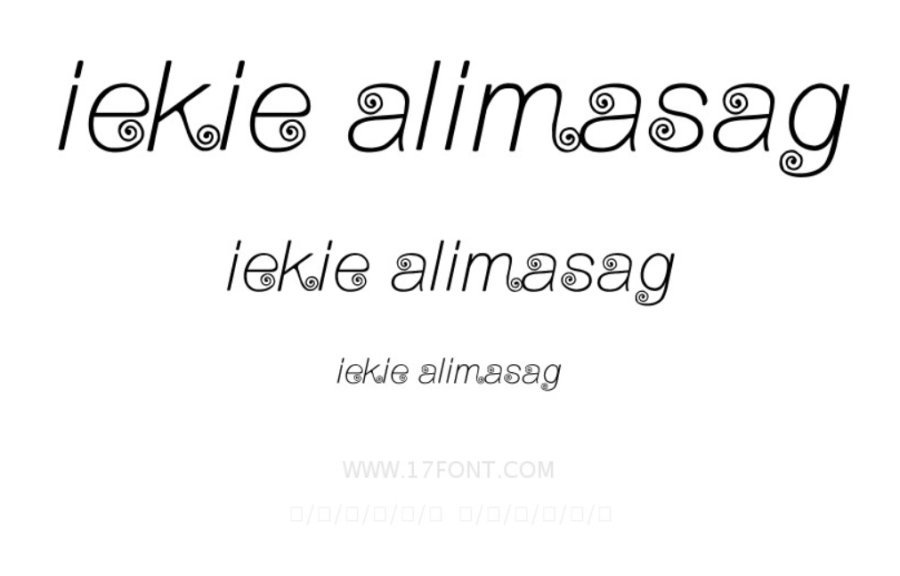
iekie Alimasag:这是一款英文花体字,在字母的收笔处添加了卷曲的创意,像茫茫大海里的漩涡,设计的很抽象化、转角平滑。适用于游戏、广告设计、动漫以及社交网络的个性化用字等领域。
熊猫大侠体:这款字体是一款中文创意花体字,以国宝熊猫作为灵感衍生出的字体风格,以黑白作为配色主体,笔画的点改为竹叶,竖变为竹子的设计别出心裁。富有创意却又不失清晰的字形易于字体识别,使人记忆犹新,过目难忘。适用于游戏、少儿类、漫画类书刊封面及正文、标志、动漫、影视,社交网络的个性化用字等领域。